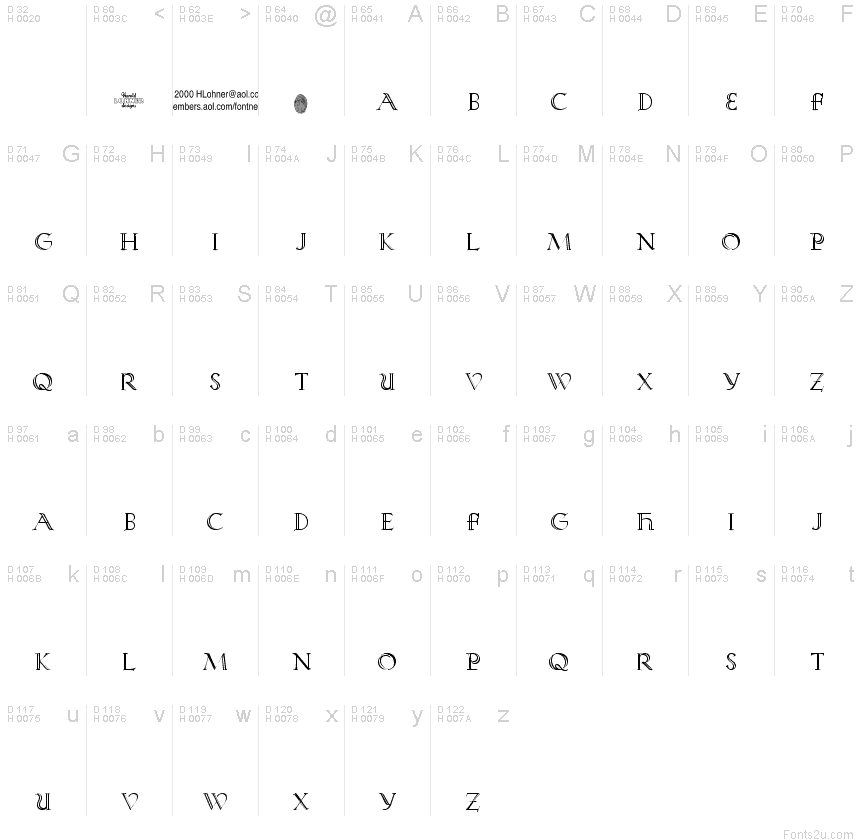
Koch Rivoli autorstwa Harolda Lohnera to bezpłatny, ozdobny krój szeryfowy w stylu retro, inspirowany oryginalnym liternictwem Rudolfa Kocha. Jego wysokie, eleganckie kształty wypełniają wewnętrzne linie, przypominające składane wstążki lub grawerowany metal, co nadaje każdej literze teatralny, niemal filmowy blask. Cienkie i grube pociągnięcia splatają się ze sobą, sprawiając, że tekst na stronie nie tylko jest widoczny, ale wręcz lśni.
Koch Rivoli zmienia krótkie słowa w logotypy: świetnie sprawdza się na okładkach książek, w identyfikacji butików, na etykietach win, plakatach vintage, zaproszeniach na wydarzenia czy ozdobnych szyldach. Odstępy zachęcają do stosowania dużych rozmiarów, więc pozwól temu darmowemu fontowi wybrzmieć w potężnych nagłówkach i znakach graficznych, a następnie zestaw go z czystym, geometrycznym krojem bezszeryfowym, aby zapewnić czytelność tekstu pomocniczego.